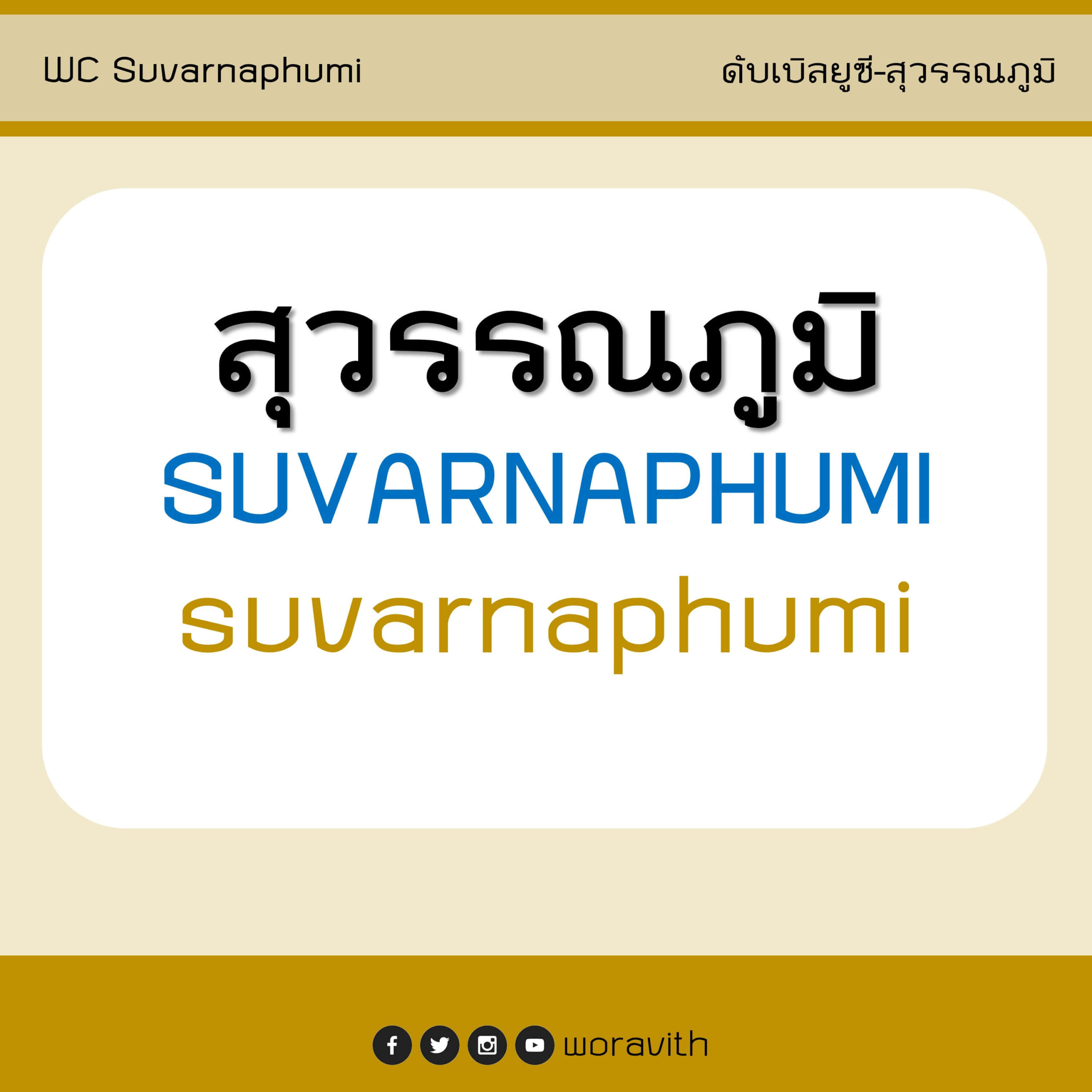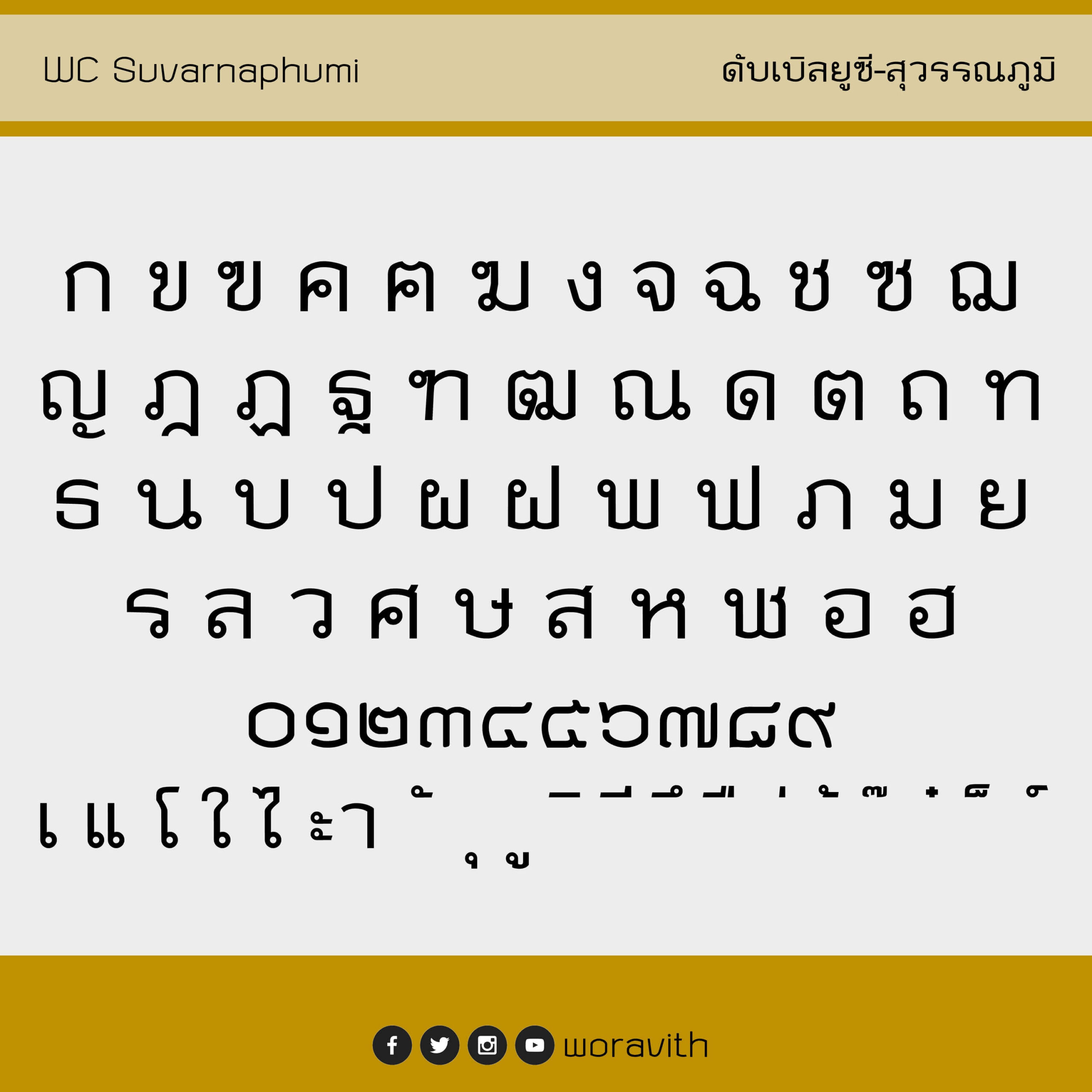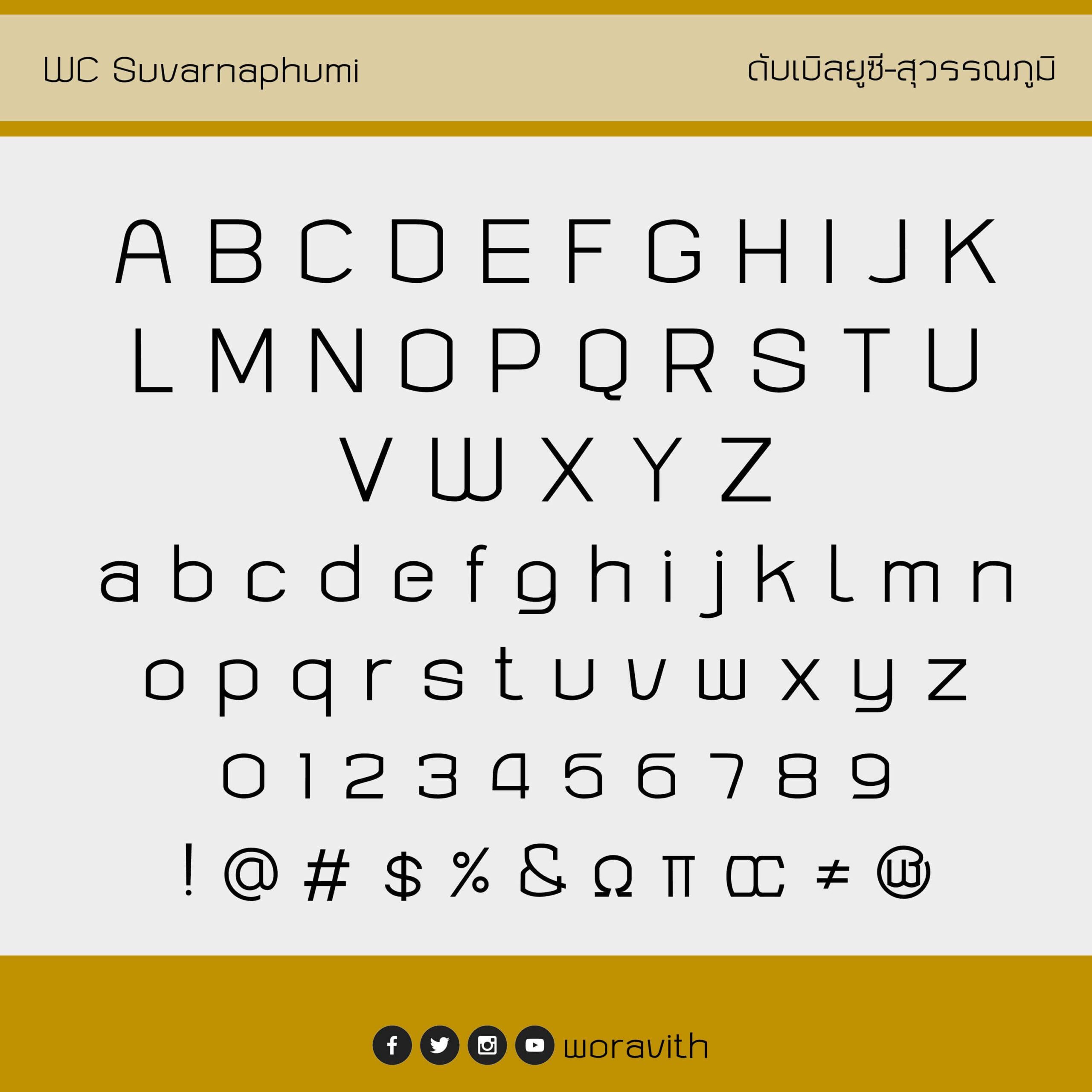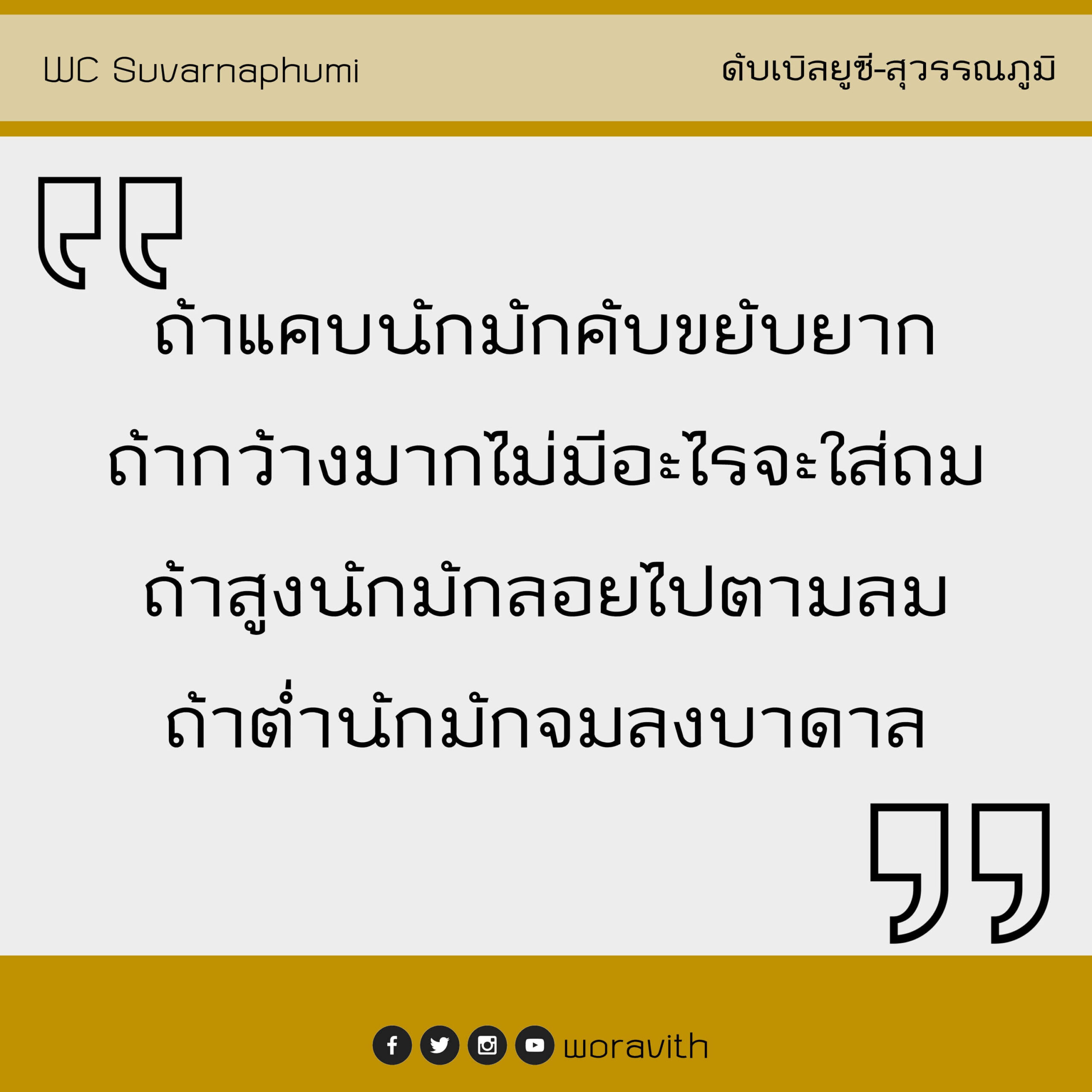
ฟอนต์ดับเบิลยูซี สุวรรณภูมิ ดัดแปลงจากฟอนต์ ดับเบิลยูซี สุวรรณชาติ เปลี่ยนตัวอักษรภาษาไทยให้เป็นอักษรหัวกลม
4 มกราคม 2567 : เพิ่มฟอนต์น้ำหนักบาง
ดับเบิลยูซี สุวรรณภูมิ (WC Suvarnaphumi)